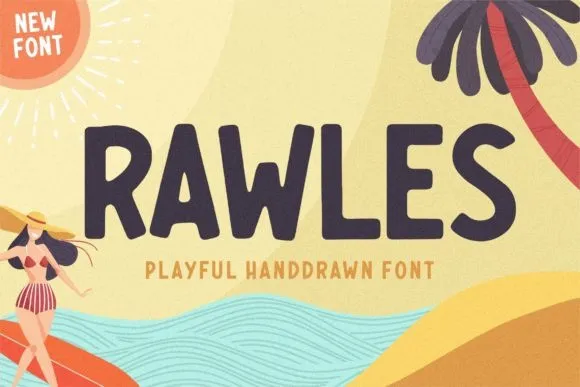
RAWLES Font – Download Grátis
RAWLES é uma fonte de display perfeita para quem procura expressar sua marca de maneira forte e chamativa. Perfeita para aplicação em embalagens de produtos, identidade visual, revistas, mídia social, festas casais ou qualquer outra ocasião que requer um toque dramático e acentuado. Seja para destacar uma mensagem acima de um fundo ou apenas personalizar textos, RAWLES garantirá seu design receber toda a atenção necessária. Esta fonte é ideal para quem busca uma maneira única de transmitir sua ideia, seja ela num layout digital ou impresso. Com o RAWLES, cada palavra ganha vida e expressão com um estilo único e poderoso.